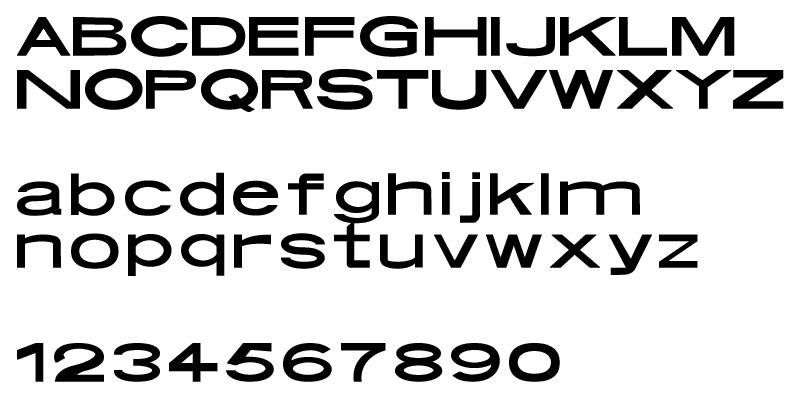
Tipografía gratuita: la tipografía de este mes ha sido diseñada por Leonardo Tavares.
La tipografía gratuita 1.617 ha sido diseñada por Leonardo Tavares.
Leonardo Tavares es un diseñador Brasileño, con una amplia experiencia en el sector del diseño gráfico. Leonardo basa sus obras en la creación de tipografías distorsionadas, algo muy diferente a lo que estamos acostumbrados a ver, y en la experimentación con estas.
Un estilo contemporáneo y muy fresco caracteriza a esta tipografía gratuita “1617”. Los caracteres que la componen son dinámicos, aunque basados en formas rectas y angulares.
La tipografía gratuita “1617” diseñada por Leonardo Tavares tiene caracteres de caja alta y caja baja.
Free typography: this month’s typography has been designed by Leonardo Tavares.
The 1,617 free typography has been designed by Leonardo Tavares.
Leonardo Tavares is a Brazilian designer, with extensive experience in the graphic design sector. Leonardo bases his works on the creation of distorted typefaces, something very different from what we are used to seeing, and experimentation with them.
A contemporary and very cool style characterizes this free typography “1617”. The characters that compose it are dynamic, although based on straight and angular shapes.
The free typography “1617” designed by Leonardo Tavares has high and low case characters.